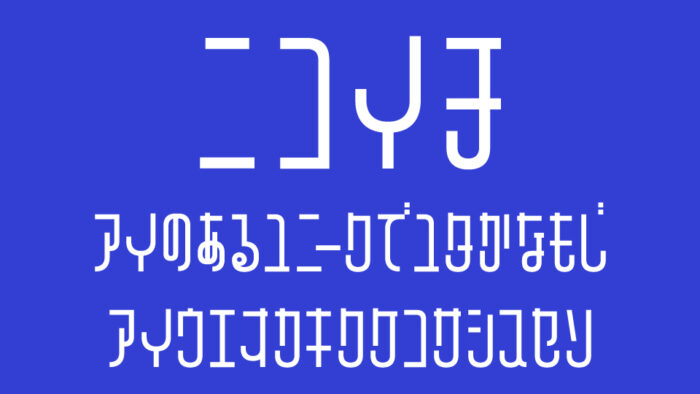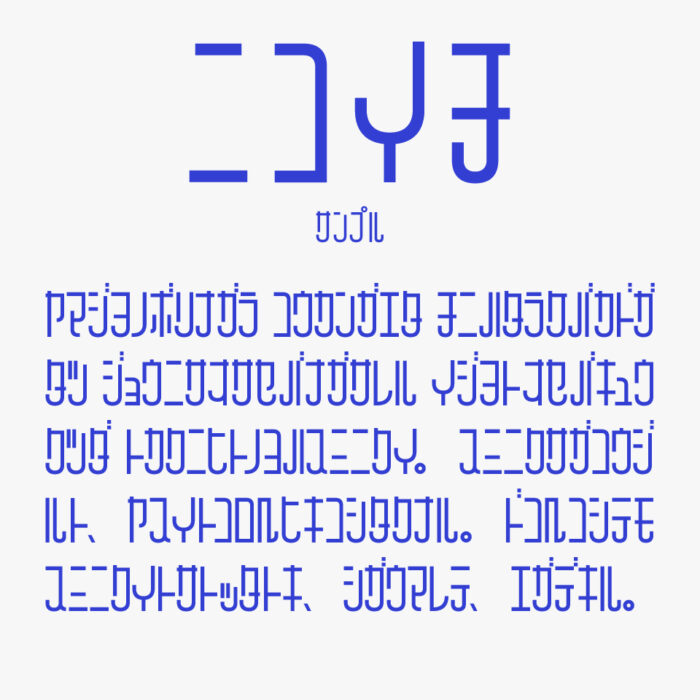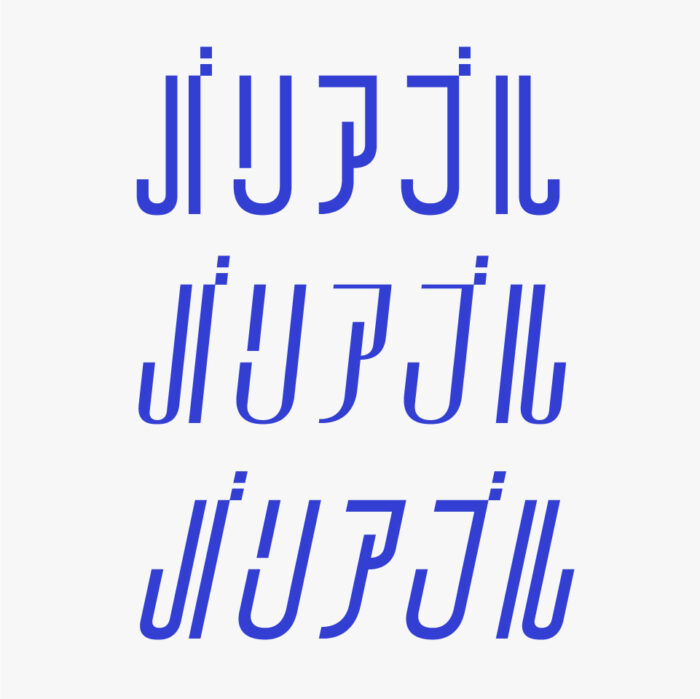
ニコイチ
ニコイチフォントは、直線をベースに構成されたユニークなフォルムが特徴で、字形・縦横線のコントラスト・傾きの3つの軸を変更できるバリアブル(可変)フォントです。
一見すると暗号のようにも見えるユニークなフォルムが、目を引くデザインとなっています。バリアブルフォントに対応しているアプリケーションであれば、字形・縦横線のコントラスト・傾きを自由に調整することが可能です。
バリアブルの数値を少し変更するだけで、1つのフォントで、さまざまな表情をもつ素敵なフォントです。